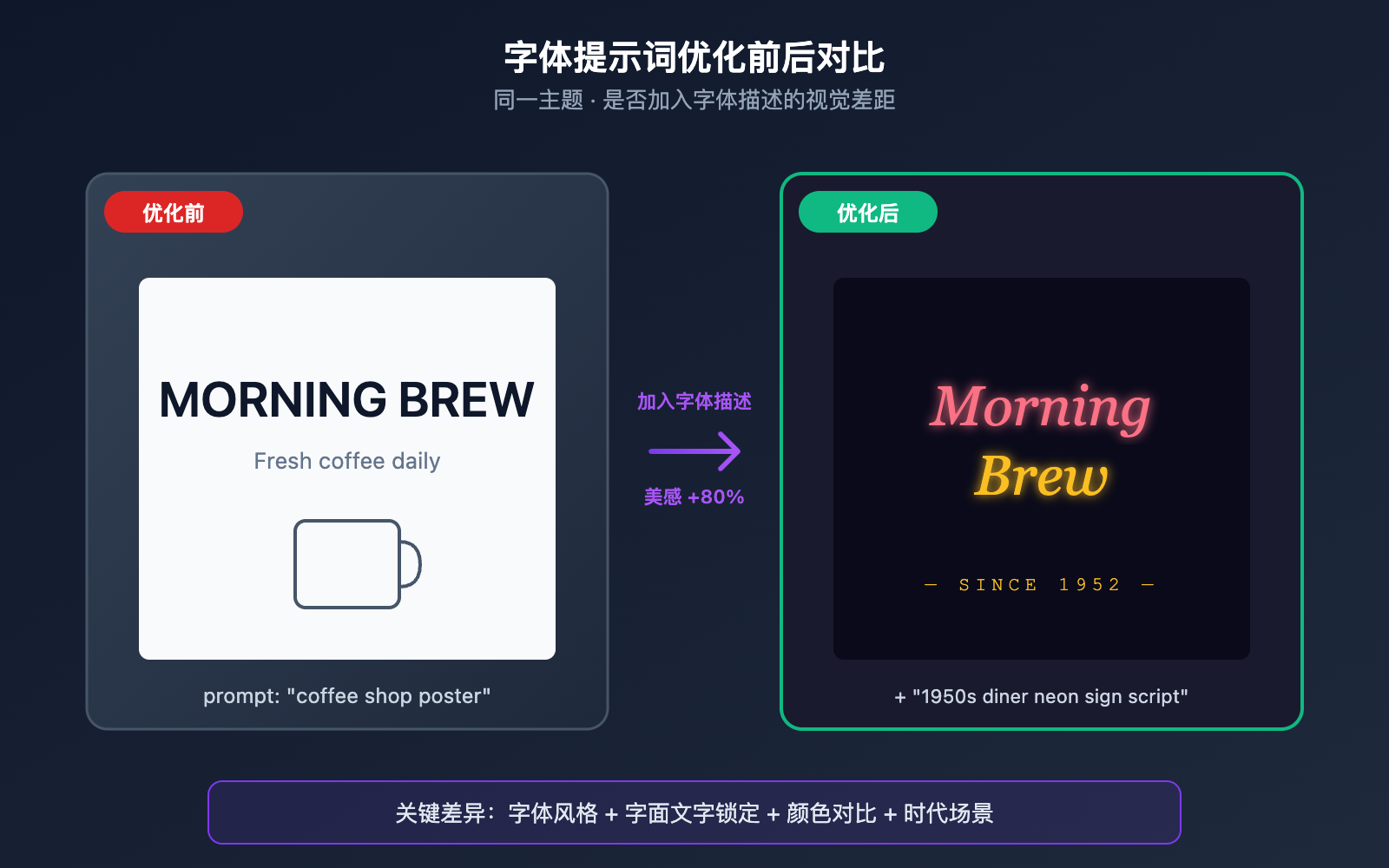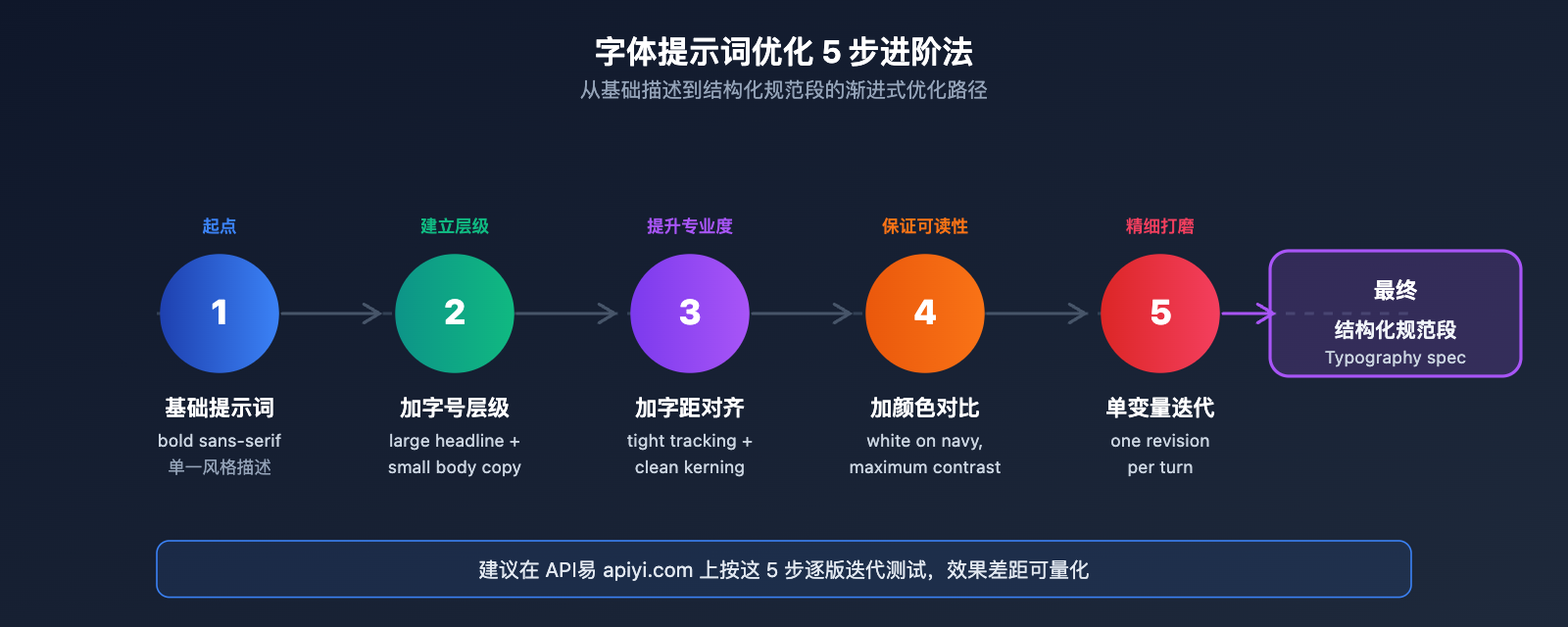
很多用户在使用 gpt-image-2 API 或 ChatGPT 官网出图时都会遇到同一个问题:模型生成的图片虽然文字识别度很高,但字体永远是那种"工程师审美"的朴素无衬线体,缺少品牌感与设计感。这种"朴素美学"在生成海报、社媒封面、产品宣传图时尤其明显,让本来不错的构图也显得廉价。
问题的根源不在于模型能力不足,而在于绝大多数用户的提示词里只描述了"画什么",却没告诉模型"字体应该长什么样"。本文基于 OpenAI 官方 Cookbook 与多家 API 服务商的实测经验,系统拆解 gpt-image-2 字体提示词的工作机制,给出 6 套可直接复用的字体描述模板,并结合 API易 apiyi.com 平台的调用示例,帮你在 5 分钟内学会让出图字体真正"有美感"的提示词写法。
一、gpt-image-2 字体提示词的核心机制
1.1 为什么默认出图字体总是朴素无衬线
gpt-image-2 在没有明确字体描述时,会根据训练数据中"最安全"的视觉先验生成字体,结果往往是中性的几何无衬线体(接近 Inter、Helvetica 风格),保证识别率但牺牲了风格化表达。
OpenAI 官方提示词指南明确指出:模型只会渲染你主动约束的视觉属性,没有约束的部分一律走默认值。也就是说,如果你只写"a poster about coffee",模型会自动选用最普通的字体;只有当你写出"hand-lettered display serif with thick brushstrokes"这种细节,模型才会触发对应的字体先验。
这就是为什么同一张主题、同一个 prompt 长度,加了字体描述与没加字体描述的成片质量可以差出一个等级。理解这一点之后,"出图字体朴素"就不再是模型缺陷,而是用户没有把字体当成图像的核心信息去描述。
另一个常被忽略的因素是模型版本。gpt-image-2 相比 1.5 代最大的升级就在文字渲染层,原生支持近 4K 输出,对小字、密集排版、多字体混排的处理能力都显著提升,这也意味着在 gpt-image-2 上花在字体提示词上的精力回报率更高,值得投入更多时间打磨。
1.2 gpt-image-2 字体提示词的四大核心要素
把"字体描述"这件事拆开看,gpt-image-2 实际上是在响应四个独立维度的指令,缺一不可:
| 要素 | 作用 | 示例描述 |
|---|---|---|
| 字体风格 (Style) | 决定字形结构与视觉性格 | bold sans-serif、condensed serif、hand-lettered display |
| 字号层级 (Hierarchy) | 控制标题/副标题/正文的对比 | large headline, small body copy |
| 颜色对比 (Contrast) | 决定字体与背景的可读性 | high contrast white on navy |
| 空间布局 (Placement) | 锁定文字位置与对齐方式 | centered at top, clean kerning |
1.3 字面文字的强约束写法
OpenAI Cookbook 的 image-gen-models-prompting-guide 给出一条关键技巧:把要出现在画面里的字符串用引号或全大写包裹起来,模型会把这部分理解为"必须按字面渲染、不能多字也不能错字"的硬约束。
实测对比下来,写 the word coffee on a sign 和写 a sign with the EXACT text "COFFEE" 出现拼写错误的概率差异显著,后者几乎能保证字符级一致。难拼的品牌名(例如 Schønne、APIYI)建议用空格隔开逐字符拼写,例如 "A P I Y I",进一步降低字符错位风险。
二、gpt-image-2 字体提示词的 6 种实战描述法
不同场景适合不同的字体描述策略。以下 6 种方法是从 OpenAI 官方示例、fal.ai 实测案例与开源 prompt 库中归纳出来的高频可复用模板。
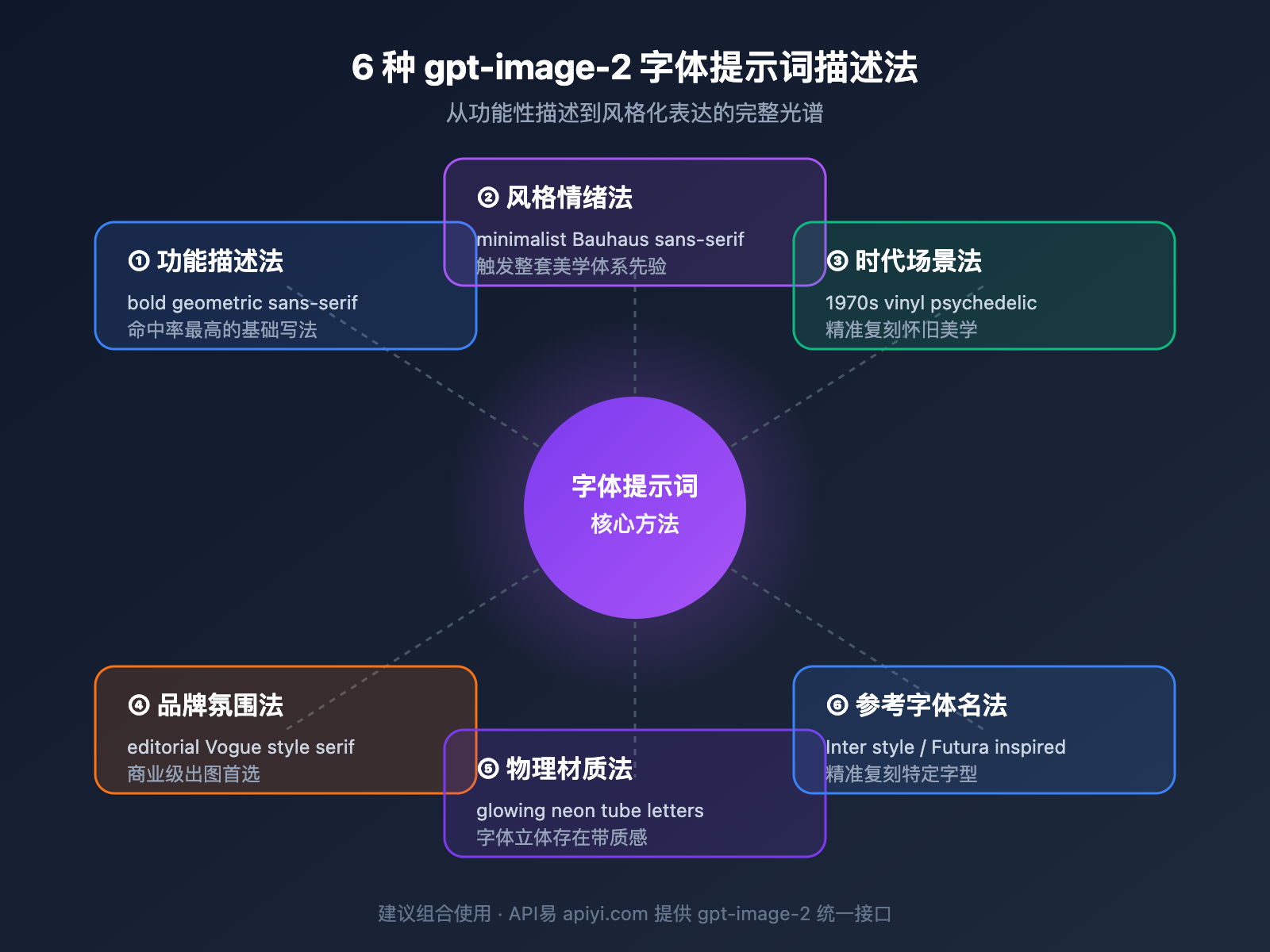
2.1 功能描述法:最稳的基础写法
直接用排印学术语描述字形特征,这是 OpenAI 官方最推荐的写法,命中率最高:
bold geometric sans-serif(厚重几何无衬线,适合科技品牌)condensed sans-serif with tight tracking(紧凑窄体,适合杂志标题)classic transitional serif with fine hairlines(精细衬线体,适合奢侈品/出版物)rounded humanist sans-serif(圆润人文无衬线,适合儿童/友好品牌)
2.2 风格情绪法:让字体有"性格"
用艺术运动或设计风格替代具体字体名,触发模型对整套美学体系的先验:
minimalist Bauhaus sans-serifArt Deco display typography with metallic strokesbrutalist concrete typographyMemphis-style 80s display font with bold geometric shapes
这种写法的好处是字体不会孤立存在,模型会自动匹配相符的颜色、版式、装饰元素,整张图的设计语言会更统一。
2.3 时代场景法:精准复刻怀旧美学
通过年代+载体的组合,让字体看起来像是从特定历史时期的真实印刷品上扫描下来:
1970s vinyl record cover psychedelic display font90s grunge zine handwritten typography with photocopy textureearly 2000s Y2K chrome bubble font1950s diner neon sign script lettering
时代场景法对生成怀旧、复古、地下文化主题的封面尤其好用,比单纯写 retro font 精准度高出一个数量级。
2.4 品牌氛围法:商业级出图首选
直接描述目标行业的视觉气质,让模型自动靠近成熟的商业字体规范:
editorial fashion magazine serif typography, Vogue styletech startup landing page typography, clean and confidentluxury skincare branding typography, refined and minimalcraft brewery label typography, hand-drawn rustic feel
2.5 物理材质法:让字体"立体存在"
把字体视为现实世界中的物理对象,而非纯数字图层。这是 fal.ai 教程里强调的高级用法:
plastic letter board with uneven letter spacing, one missing slotglowing neon tube letters with visible glass tubing and cablescut paper letters with soft drop shadows, layered cardboardchiseled marble inscription with deep shadow inside the cuts
物理材质法生成的字体会自带光照、阴影、磨损细节,质感远超平面贴字。
2.6 参考字体名法:精准复刻特定字型
虽然 OpenAI 官方没有公开支持的字体白名单,但实测主流知名字体名是可以被识别的,作为辅助修饰词加在功能描述后效果最好:
clean sans-serif typography, Inter styleeditorial serif similar to Playfair Displaygeometric sans-serif inspired by Futurahumanist serif in the vein of Garamond
注意这种写法是风格暗示而非字符级复刻,模型不会真的调用字体文件,但视觉感觉会非常接近。
| 描述法 | 适用场景 | 命中率 | 风格丰富度 |
|---|---|---|---|
| 功能描述法 | 通用、UI、企业 | ⭐⭐⭐⭐⭐ | ⭐⭐⭐ |
| 风格情绪法 | 海报、艺术、个性品牌 | ⭐⭐⭐⭐ | ⭐⭐⭐⭐⭐ |
| 时代场景法 | 复古、怀旧、文化主题 | ⭐⭐⭐⭐ | ⭐⭐⭐⭐⭐ |
| 品牌氛围法 | 商业、电商、广告 | ⭐⭐⭐⭐ | ⭐⭐⭐⭐ |
| 物理材质法 | 立体场景、产品摄影感 | ⭐⭐⭐ | ⭐⭐⭐⭐⭐ |
| 参考字体名法 | 精准复刻、设计师场景 | ⭐⭐⭐ | ⭐⭐⭐⭐ |
三、gpt-image-2 字体提示词的 API 实战调用
理解了描述方法之后,下一步是怎么把这套提示词传给 gpt-image-2 API。这一节给出最简调用代码与关键参数说明。
3.1 极简调用示例:让字体提示词生效
下面这段 Python 代码使用 OpenAI SDK 调用 gpt-image-2,字体提示词放在 prompt 主体里即可生效:
注意 prompt 里同时包含了"画什么 + 字面文字 + 字体描述 + 颜色对比 + 位置"五个维度,这是高质量出图的最小完备结构。
3.2 关键参数:quality 对字体清晰度的影响
gpt-image-2 的 quality 参数对小字、密集排版、多字体混排的影响远大于对画面整体观感的影响:
| quality 等级 | 适用场景 | 字体清晰度 | 渲染速度 |
|---|---|---|---|
| low | 草图/快速预览 | 仅大标题清晰 | 最快 |
六、总结:让 gpt-image-2 字体真正有美感的关键路径
回到开头的问题——为什么 gpt-image-2 出图字体总是朴素无美感?答案是:模型只渲染你主动约束的属性。一条专业级字体提示词必须同时覆盖字体风格、字号层级、颜色对比、空间布局四要素,再叠加引号锁定字面文字、quality 参数设为 high、必要时配合参考图。
本文给出的 6 种描述法(功能描述、风格情绪、时代场景、品牌氛围、物理材质、参考字体名)覆盖了绝大多数商业出图场景。建议先从功能描述法上手,逐步叠加风格情绪与品牌氛围,最后用结构化字体规范段固化下来作为团队复用模板。
字体不是图像的装饰,而是图像的灵魂。掌握 gpt-image-2 字体提示词的写法,本质上是把"提示词工程"从画面构图层面延伸到排印设计层面,这也是 AI 图像生成从"能看"走向"专业级"的关键一跃。